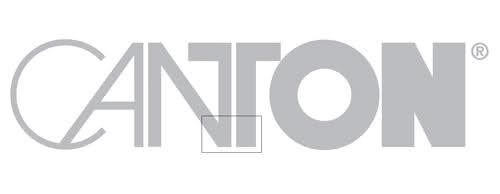
Das lustige Sommerloch-Ratespiel 2009
Die sind 200% anthro, schau dir mal die Site an.
...ich tanz mir ein Blau!
Ich hab hier übrigens noch ganz olle Stifte liegen, die sind komplett mit der Futura beschriftet, inklusive ft-Ligatur ...
Schwartau. Die mit der Marmelade aus der Lübecker Bucht ...
respekt, das hätt ich nie erkannt. kauf ich aber auch nicht, hier ist man Mühlhäuser ;)
stockmar habe ich auch noch nie gesehen. :(
Das glaube ich Dir auf’s Wort! :mrgreen:
Wobei ich ja sagen muß: Die Farben von Stockmar sind unschlagbar. Insbesondere hierzulande habe ich nicht ein einziges Wachsmalset gesehen welches auch nur ein annähernd so schönes Ultramarinblau oder Karminrot gehabt hätte. Für die Kinder macht das vermutlich nicht gar einen so großen Unterschied beim malen, aber mir brennen diese Neon-Wachsstiftfarben immer die Augen aus … :twisted:
hä? :? ich kannte nur diese "crayons" stifte, falls ich mal paar kinder geschenkt bekomme,
werd ich denen paar stockmars kaufen, damit sie über ihren getanzten namen malen können. ;)
Man kriegt sie zwar bei Amazon aber ansonsten laufen einem die wirklich nur in Waldorfschulen oder anthroposophischen Buchläden über den Weg. Und wenn man an diesen Orten schon mal ist (Schüler ausgenommen), dann schaut man sich normalerweise andere Dinge an als ausgerechnet Wachsmalstifte.
Man kann damit übrigens auch ganz un-anthroposophisch malen. :lol:
Produkte der gesuchten Firma, sofern sie ein »Reference« im Produktnamen haben, machen schon mehr Spaß als Sachen von Trigema.
… hier ist man Mühlhäuser …
Aha. Ich dachte, bei Euch ist man Pirnaer.
Wer Einträge nachmacht oder verfälscht oder nachgemachte oder verfälschte sich verschafft und in Verkehr bringt, wird mit Zuchthaus nicht unter zwei Jahren bestraft. Außerdem: Wenn schon, dann bringt es nichts, das Citat zu ändern und das Citierte Original stehenzulassen. :huhu:
Ich hatte die sowohl in der öffentlich-rechtlichen Grundschule als auch auf dem staatlichen Gymnasium, beides seinerzeit in Bremen, damals noch Paradies der Lehr- und Lernmittelfreiheit. In der Grundschule gab's sogar die Wachstafeln zum Kneten.
Als Kind hatte ich beides: nordamerikanische Crayola und Stockmar. Haben war bei Crayola besser (soooo viele Farben), Malen bei Stockmar (wenige, aber leuchtende Farben auf dem Papier, tolles Malverhalten).
unetrhaltungselektronik ist aber das richtige feld? lautsprecher, boxen etc.?
Ja